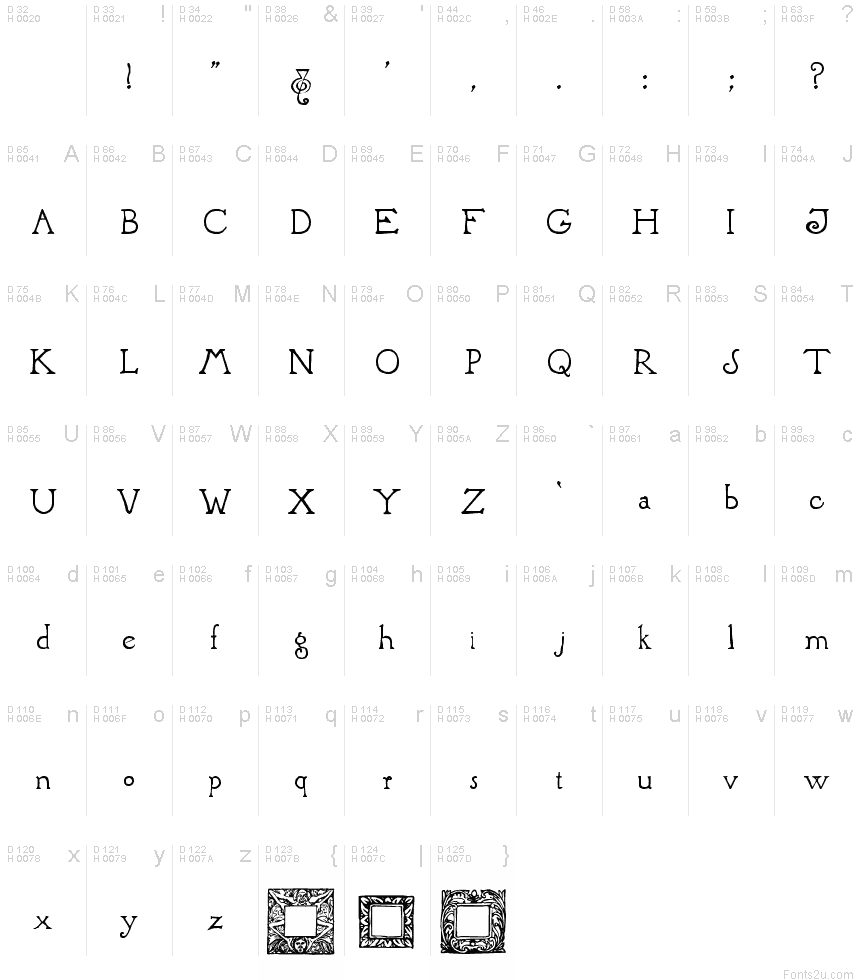
Brandywine, zaprojektowany przez Davida F. Nalle z Scriptorium Font Library, to darmowy, retro font typu display z duszą wyjętą wprost z baśni. Jego lekko nierówne kreski, zakręcone zakończenia i subtelnie zwężone łuki sprawiają wrażenie odręcznego pisma, niczym z dawnej mapy fantasy lub klasycznej książki dla dzieci. Tekstura jest urzekająco organiczna, nadając tytułom i logotypom ciepły, rzemieślniczy charakter, przy zachowaniu pełnej czytelności w średnich rozmiarach.
Brandywine dodaje szczyptę literackiej magii projektom okładek książek, etykietom browarów, grom fantasy, menu kawiarnianym, plakatom czy identyfikacji wizualnej butików. Ten darmowy font najlepiej sprawdza się w nagłówkach lub krótkich hasłach, zwłaszcza w zestawieniu z czystym, dyskretnym krojem bezszeryfowym w tekście głównym.